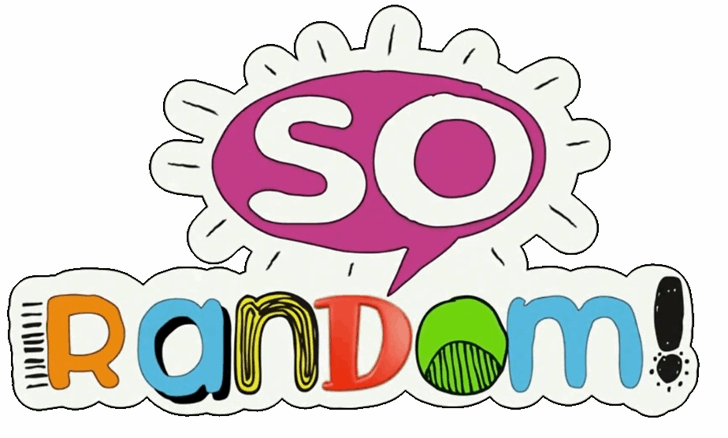
A fonte ‘So Random!’ é uma criação inspirada no logotipo da segunda temporada do famoso programa de comédia ‘So Random!’, exibido na série Sonny With A Chance. Com letras vibrantes e variadas, essa fonte retrata perfeitamente o tema do show sobre a aleatoriedade. Fãs de Sonny With A Chance certamente apreciarão as opções criativas que a So Random! oferece. Hamilton é o designer responsável por essa font original e única. Como ela não possui direitos autorais, a fonte não foi baseada em nenhum design específico ou propriedade intelectual existente.